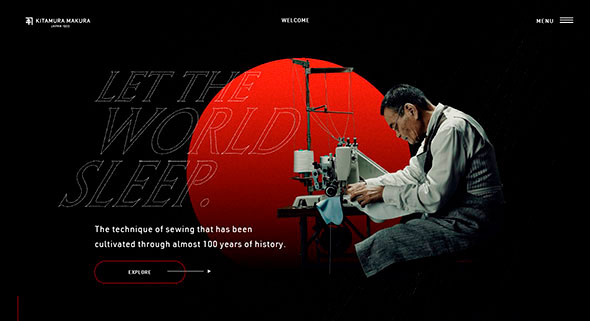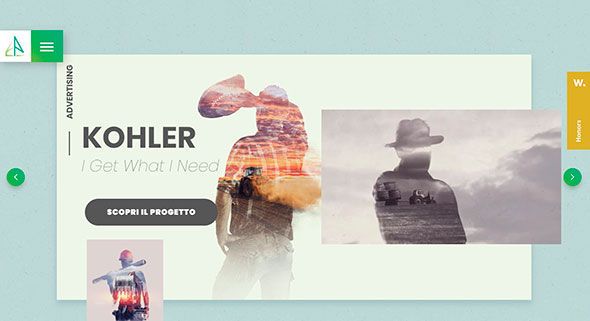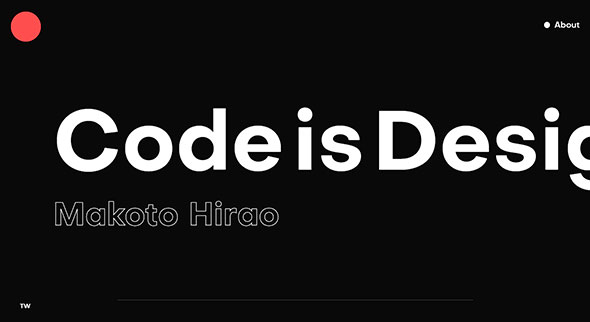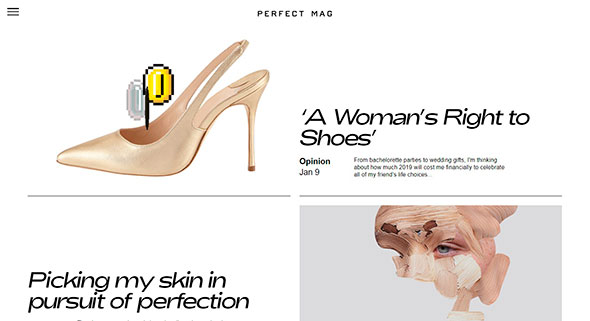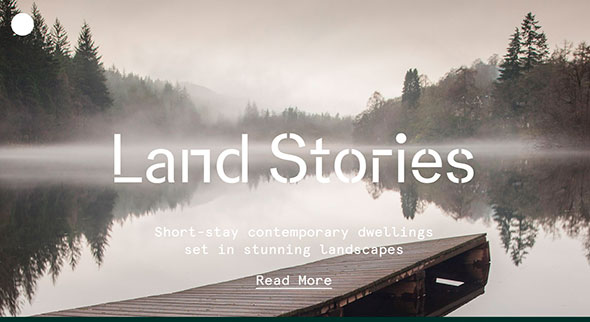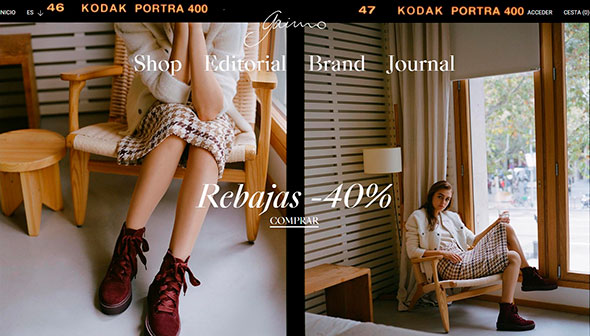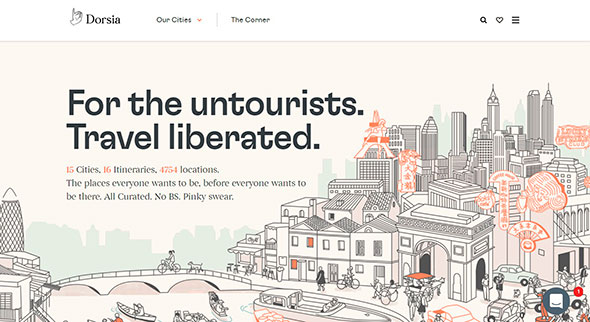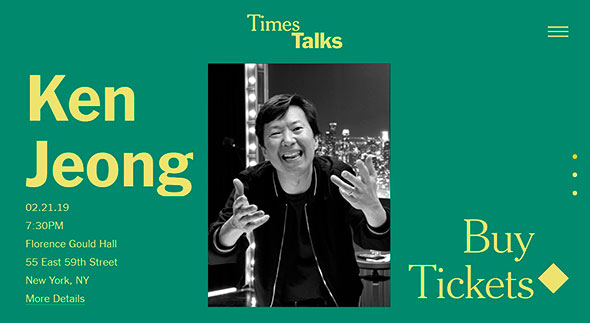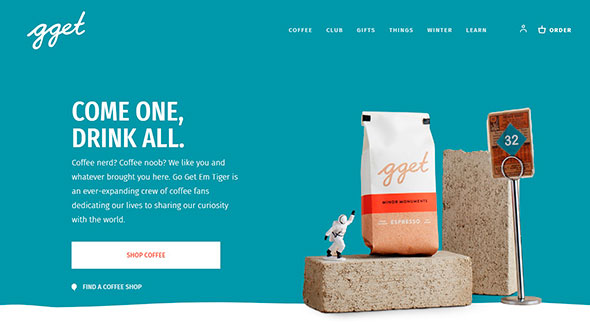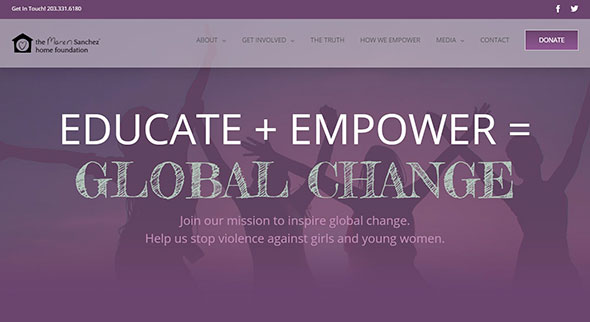
Разные шрифты на одной веб-странице
Еще не так давно веб-дизайнерам советовали не использовать больше двух, а лучше одного шрифта на странице. Но эти времена прошли, и сегодня можно практически все. Разные начертания стоят рядом, переплетаются и подчеркивают индивидуальность дизайна. Сегодня мы собрали примеры того, как разные шрифты используются на одной странице.